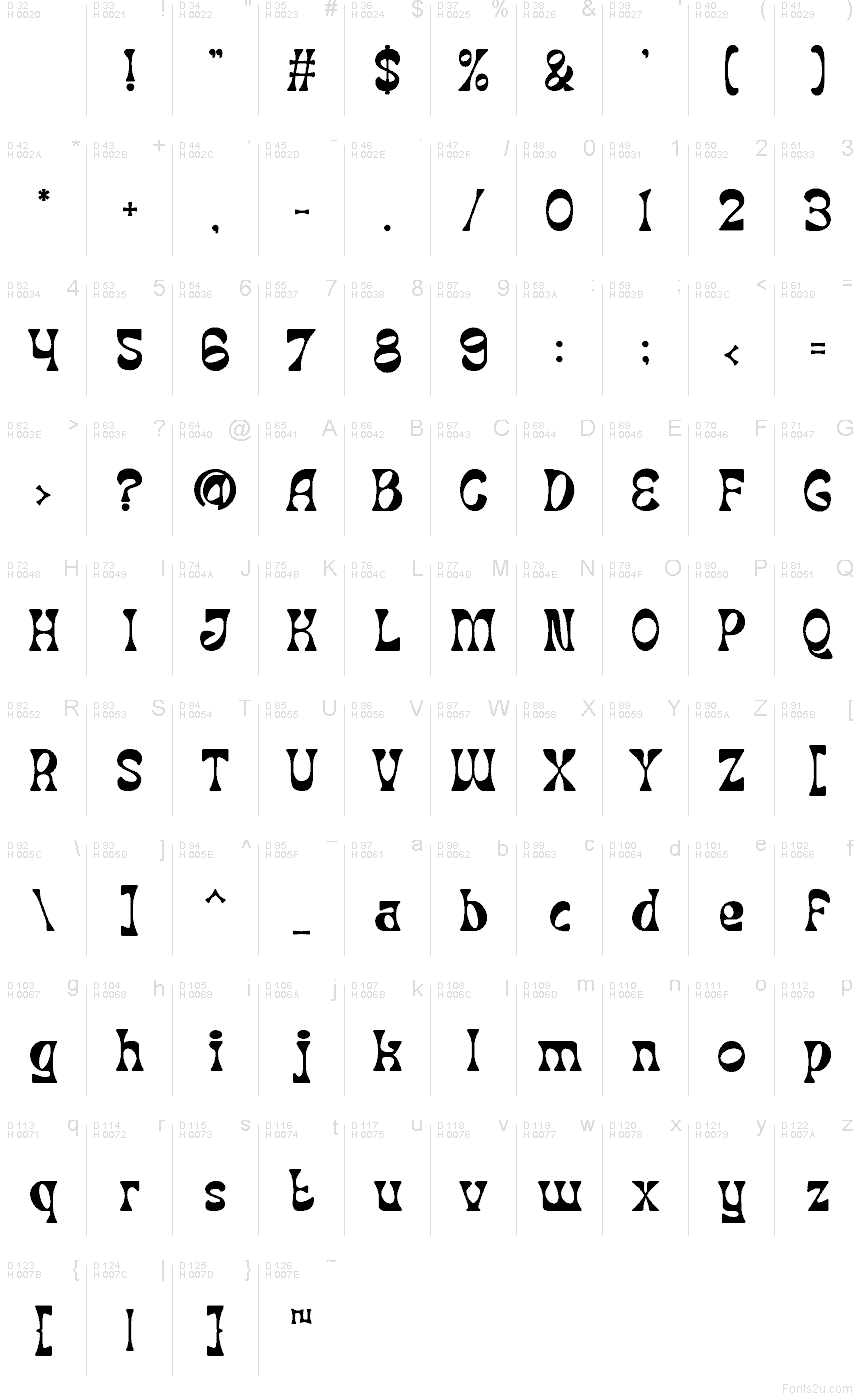
Mind Meld One di Putracetol Studio è un font display gratuito e groovy, con quel tocco psichedelico tipico della fine degli anni '60. Le lettere si allungano in morbide forme a clessidra con grazie pesanti e fuse e giunzioni strette, rendendo l'intero font ondulato, sognante e leggermente ipnotico, senza perdere la sua silhouette decisa.
Si adatta perfettamente a poster, grafiche musicali, branding di caffè rétro, volantini per eventi e titoli, dove una frase breve può sfruttare questo ritmo fluido. Essendo un font gratuito, funziona benissimo anche per titoli e loghi, poiché i centri schiacciati e le cime arrotondate, che si ripetono, fanno sì che anche le parole più semplici sembrino parte dello stesso groove visivo.